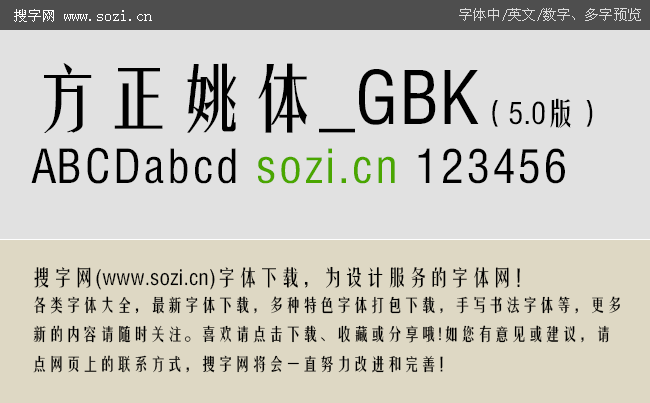
方正姚體-GBK
搜字網(wǎng)給大家提供一款適合排版的中文美術(shù)字體方正姚體下載。方正姚體字體雋秀工整,結(jié)構(gòu)狹長,字間距較大,排印清晰,整齊劃一,被稱為“姚體”。GBK編碼共收錄了21003個漢字,完全兼容GB2312-80標(biāo)準(zhǔn),適用于書籍、報刊、雜志的標(biāo)題字。